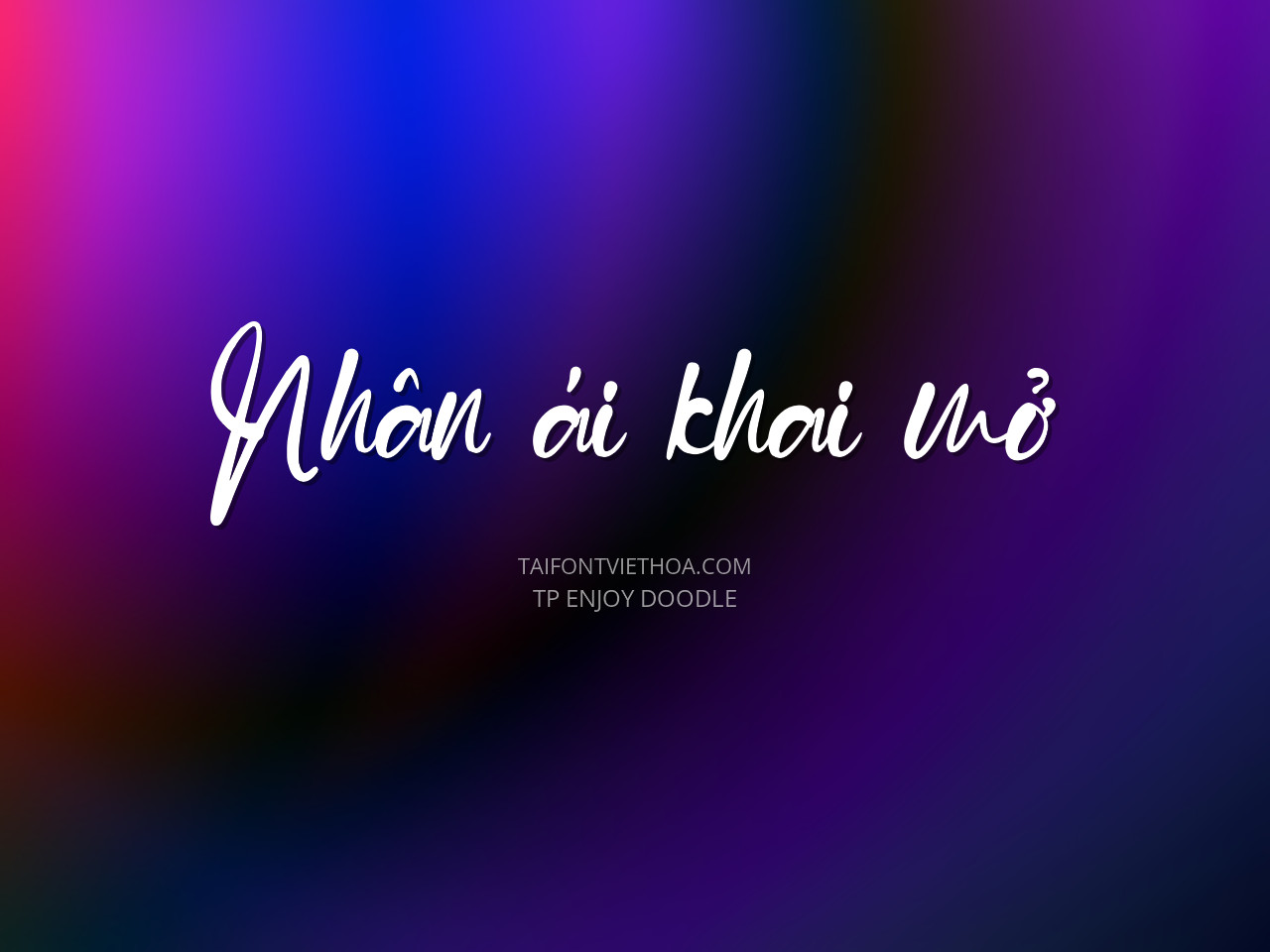
Giới thiệu về font TP Enjoy Doodle Regular – Kiểu chữ handwritten vui nhộn, thân thiện và sáng tạo
TP Enjoy Doodle Regular là phiên bản Việt hóa của font Enjoy Doodle – một kiểu chữ handwritten mang phong cách vui nhộn, thân thiện và rất sáng tạo. Font được thiết kế với các nét chữ cong cong, mềm mại và tự nhiên, tạo cảm giác gần gũi và trẻ trung, rất phù hợp cho các dự án thiết kế poster, thiệp, bao bì và các sản phẩm sáng tạo dành cho giới trẻ.
Phiên bản Việt hóa của TP Enjoy Doodle Regular đã được Taifontviethoa.comchăm sóc kỹ lưỡng, hỗ trợ đầy đủ dấu tiếng Việt cùng nhiều ngôn ngữ khác. Font giúp các nhà thiết kế dễ dàng áp dụng trong nhiều dự án sáng tạo với phong cách vui nhộn, trẻ trung và đầy màu sắc.
Thiết kế viết tay mềm mại – Lý tưởng cho thiết kế trẻ em và truyền thông năng động
TP Enjoy Doodle Regular sở hữu các nét chữ cong cong, uyển chuyển và tự nhiên, tạo nên cảm giác vui vẻ, sinh động và thu hút. Font rất phù hợp cho tiêu đề, poster, bao bì sản phẩm hoặc các phần thiết kế cần sự nổi bật và thân thiện. Phong cách thiết kế của Enjoy Doodle rất thích hợp với các dự án giáo dục, giải trí, quà tặng và truyền thông dành cho giới trẻ.
Ứng dụng lý tưởng: thiết kế poster, thiệp, bao bì sản phẩm, bài đăng mạng xã hội và các dự án sáng tạo cần phong cách vui tươi, thân thiện. Ngành nghề phù hợp: giáo dục, giải trí, quà tặng, truyền thông trẻ em và thương hiệu năng động.